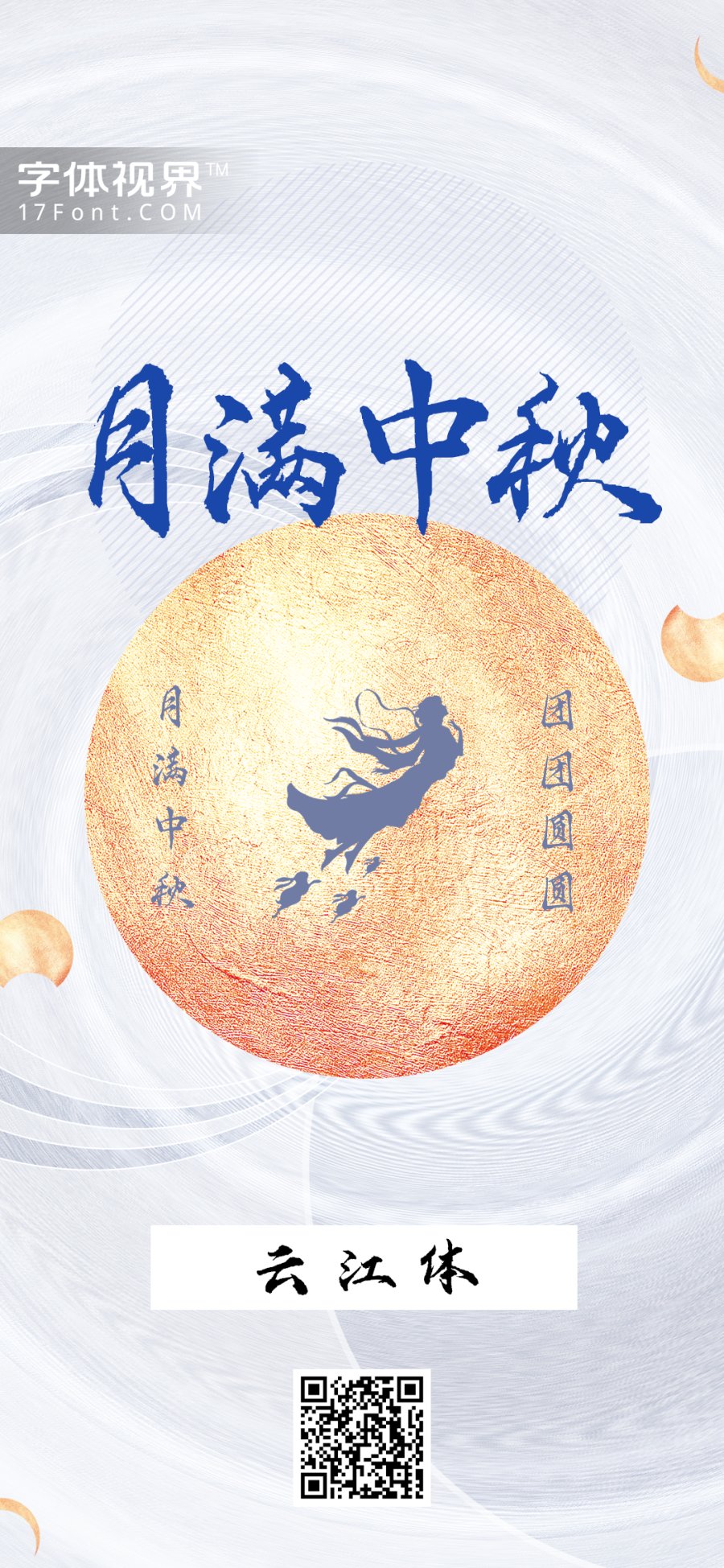
还在为了找字体而头疼吗?今天给大家推荐一款个人免费商用的书法字体-云江体,
该字体由著名字体设计师何云老师耗时1年独自完成创作,由字体视界对外公开首发,供个人免费商用;
云江体字体笔势婉转灵动且流畅自然,具有独特的韵味,又有独特的文化魅力及笔意境界。笔画细致流畅,结构紧凑,笔意拙中带巧,不避锋芒。适用于封面设计、海报宣传、书籍排版等场景中。
云江体